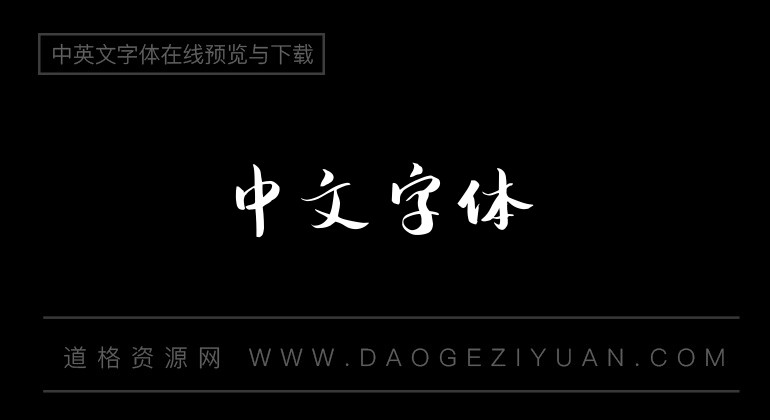
Aa卑微的我喜欢遥远的你是一款非常特别的字体,它融合了中国传统的汉字笔画和欧洲风格的文字结构,让字体看起来更加柔美可爱。它的字形更加柔和,比较特别,有一种温柔的感觉,能够表达出强烈的情感。它的字体比较细,线条流畅,比较细腻,也比较纤细,能够表达出温柔的情感。文件名:AaBeiWeiDeWoXiHuanYaoYuanDeNi-2.ttf
Aa卑微的我喜欢遥远的你是一款非常不错的手写艺术字体,具有很好的视觉感,适合于文化类的宣传设计、商业类品牌的广告和产品包装设计以及个性化文字排版等较多场景。